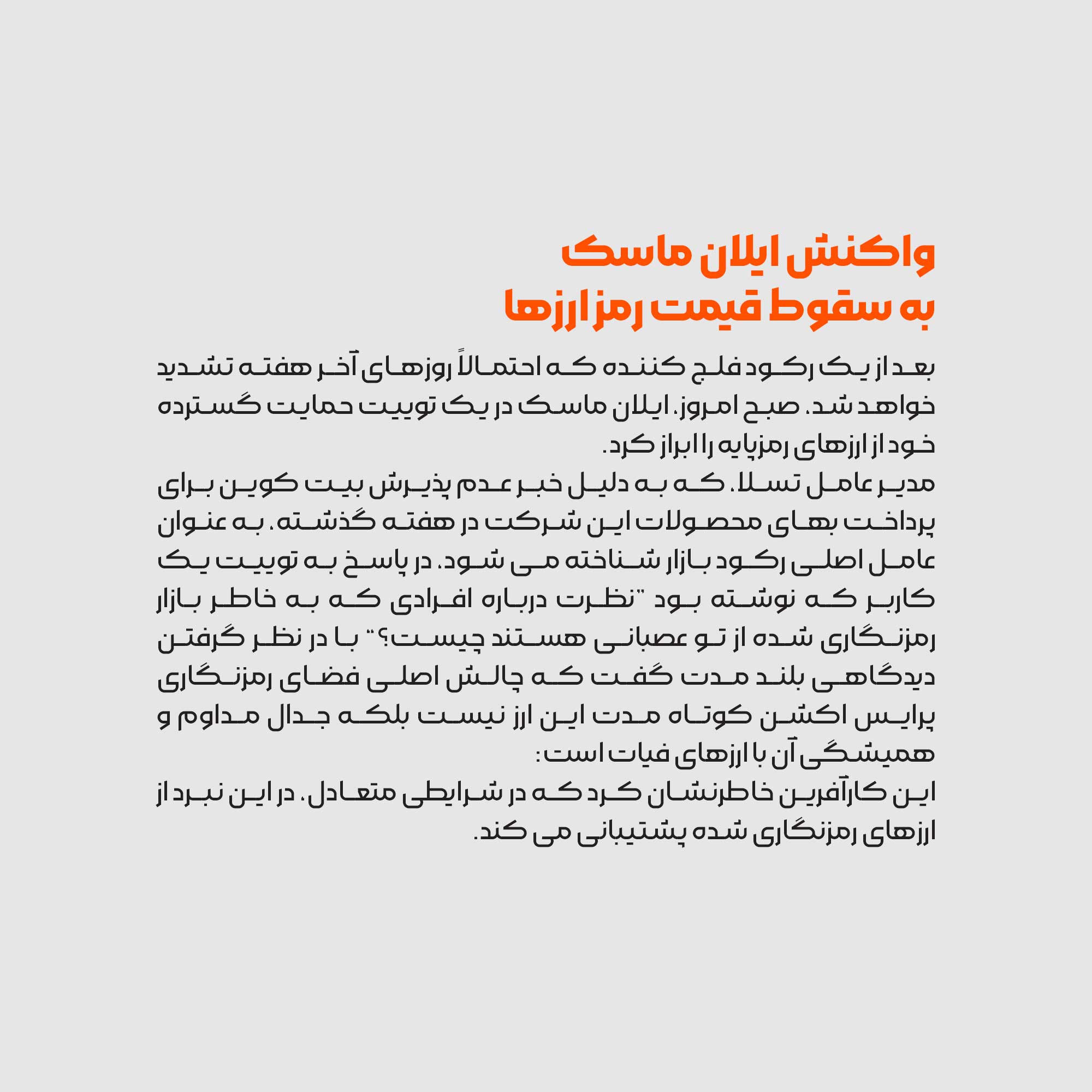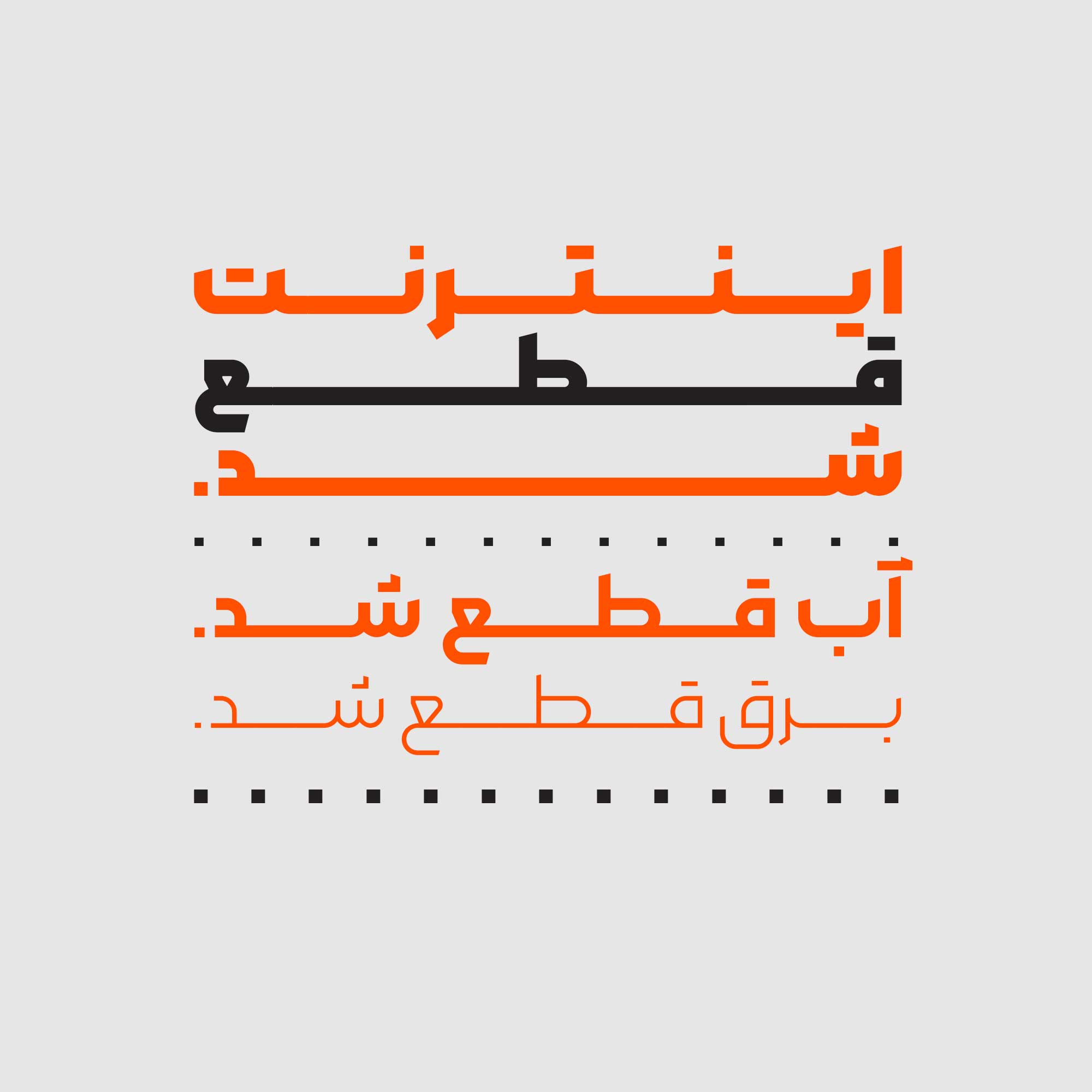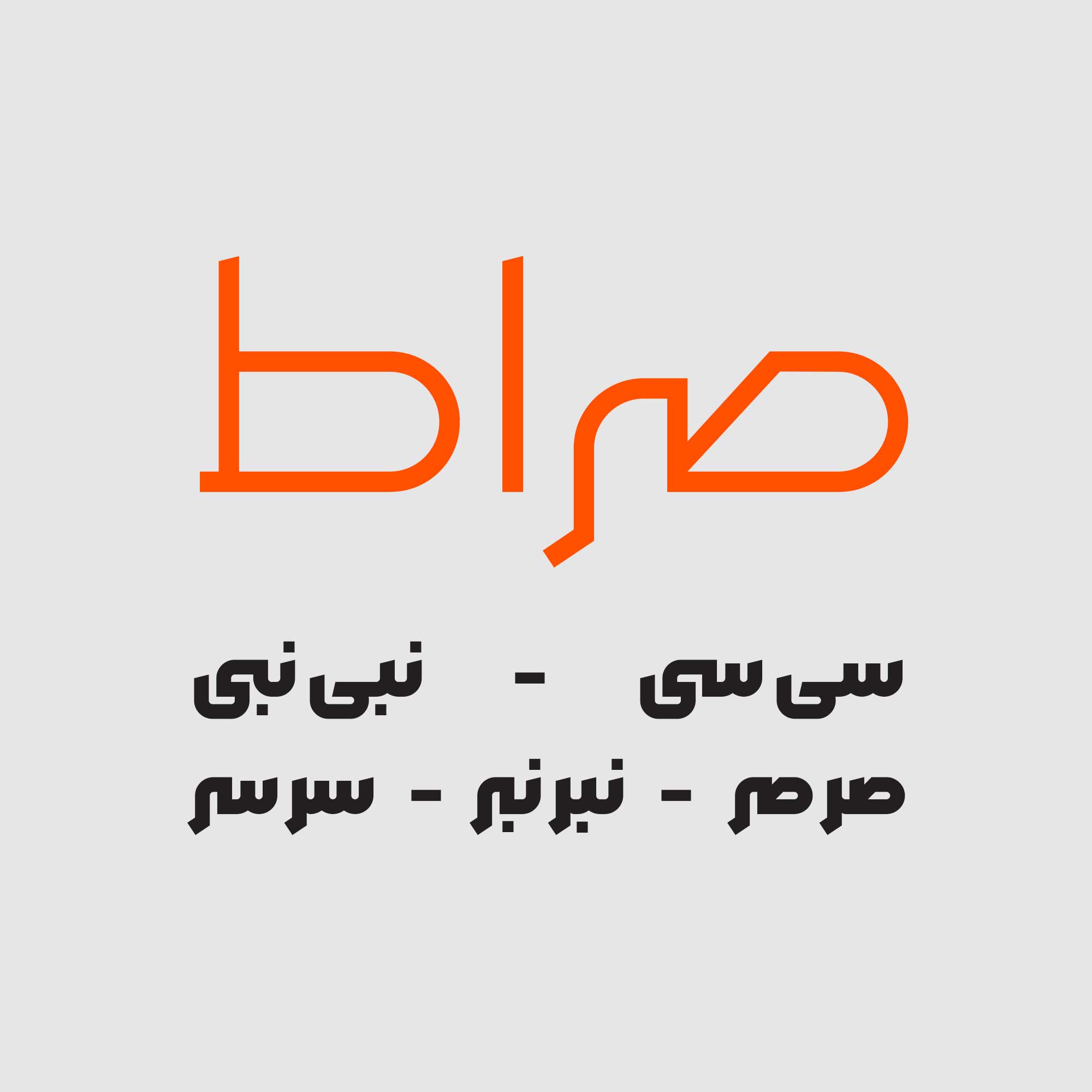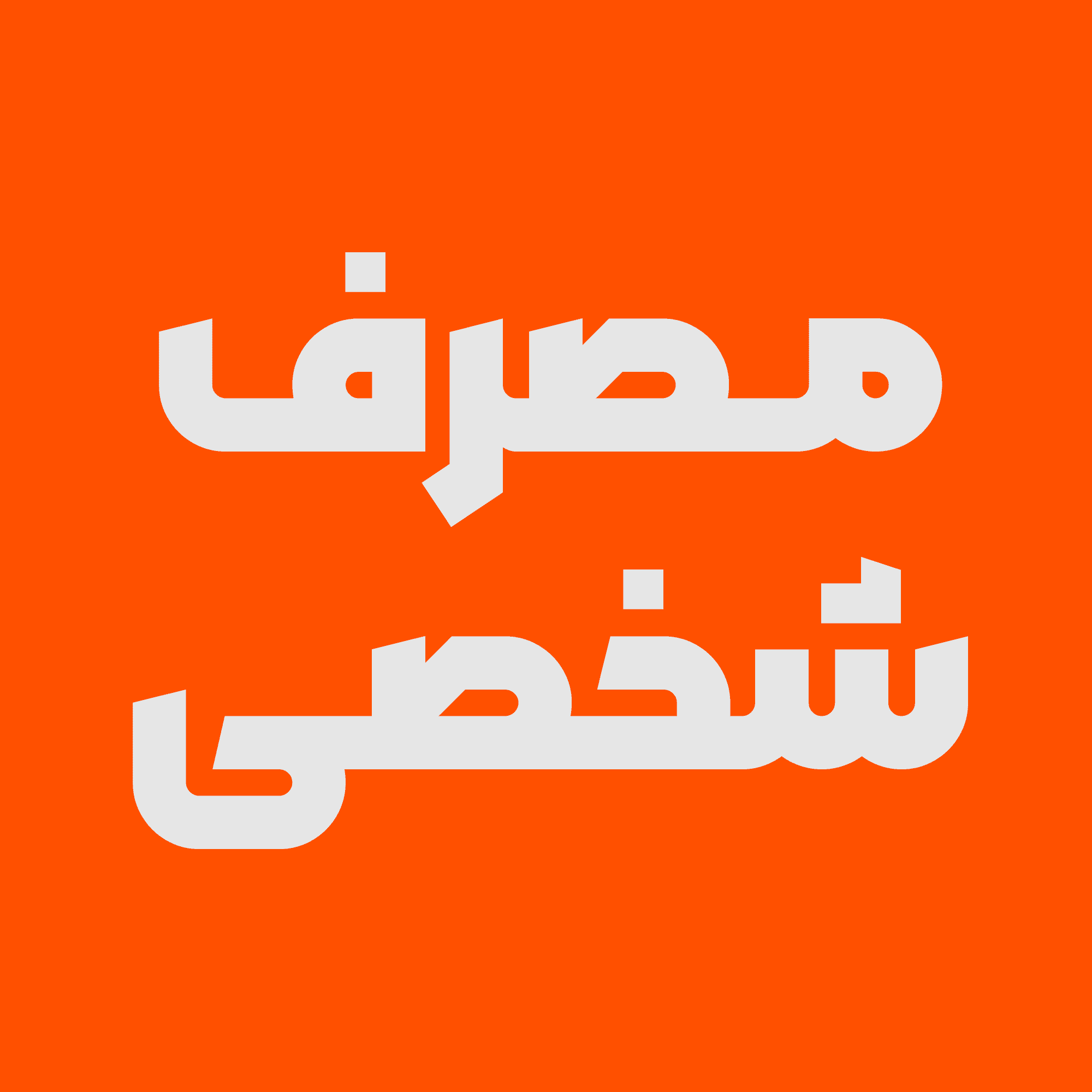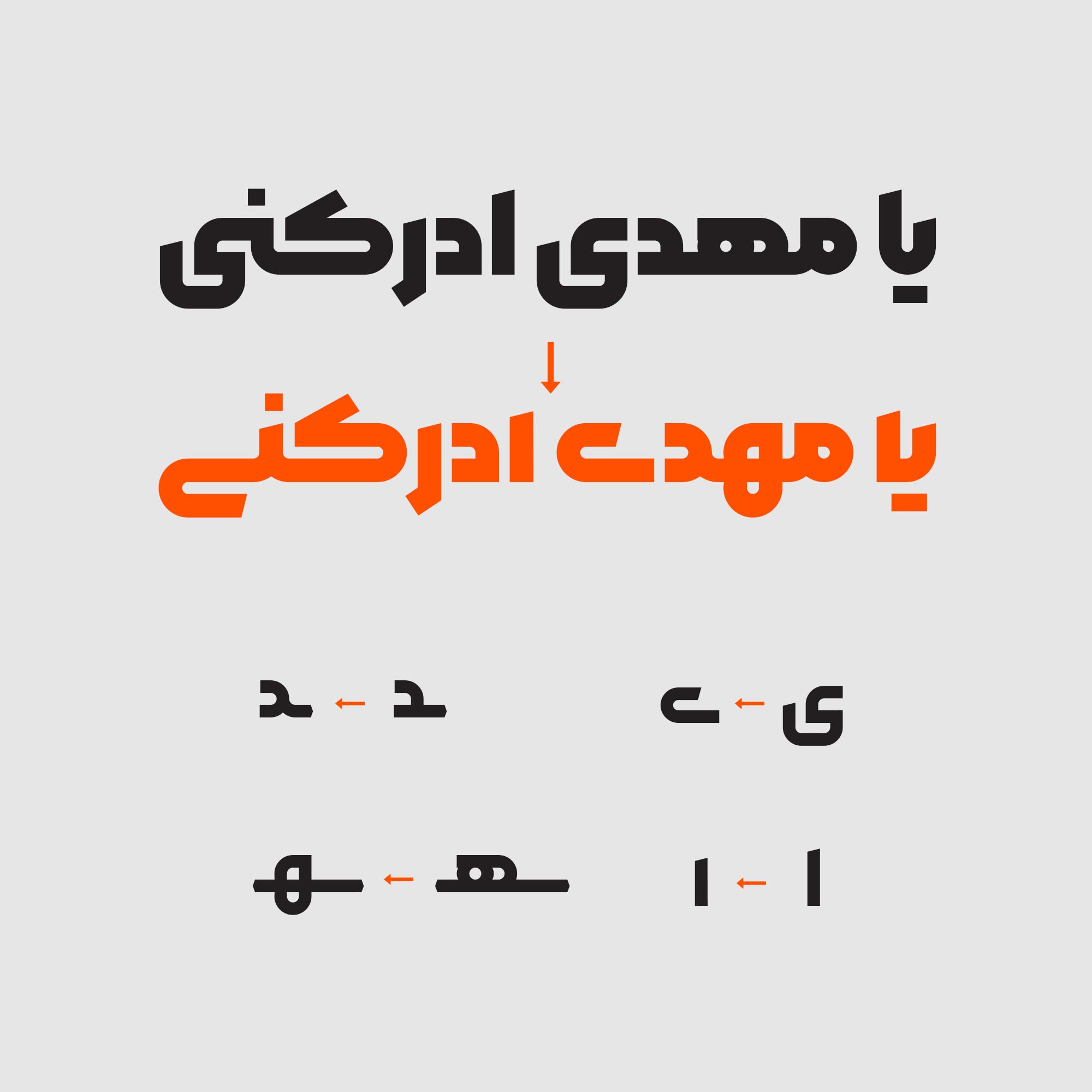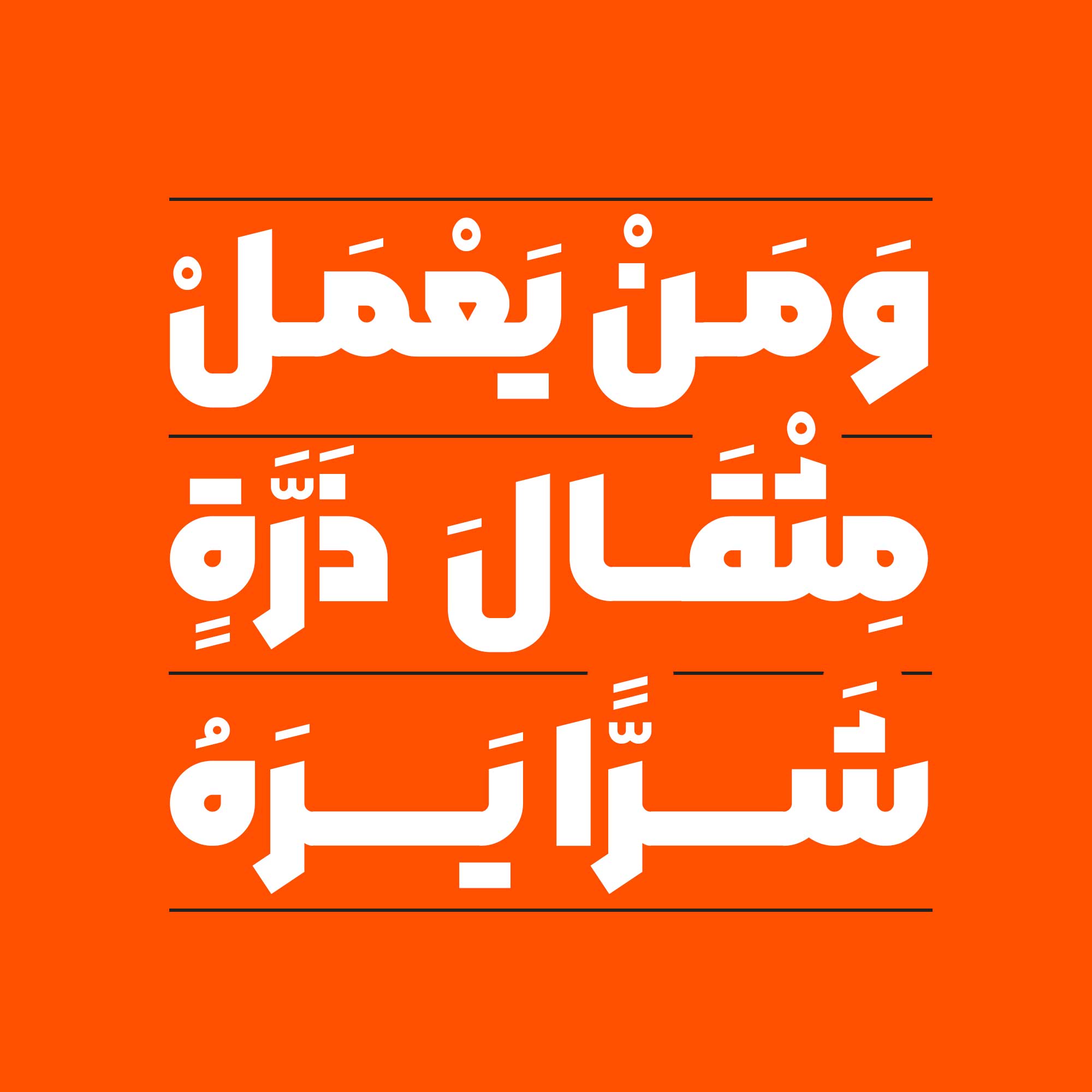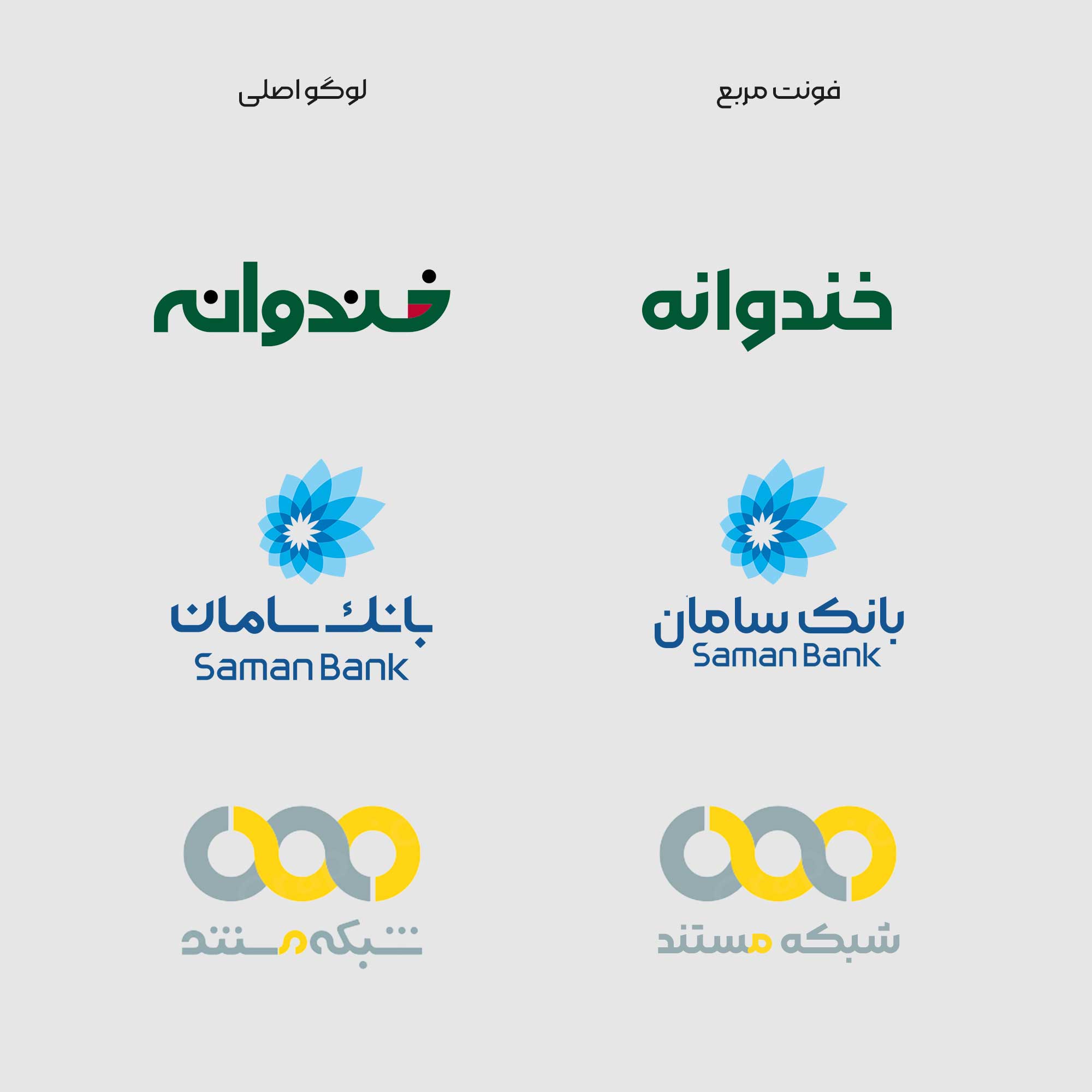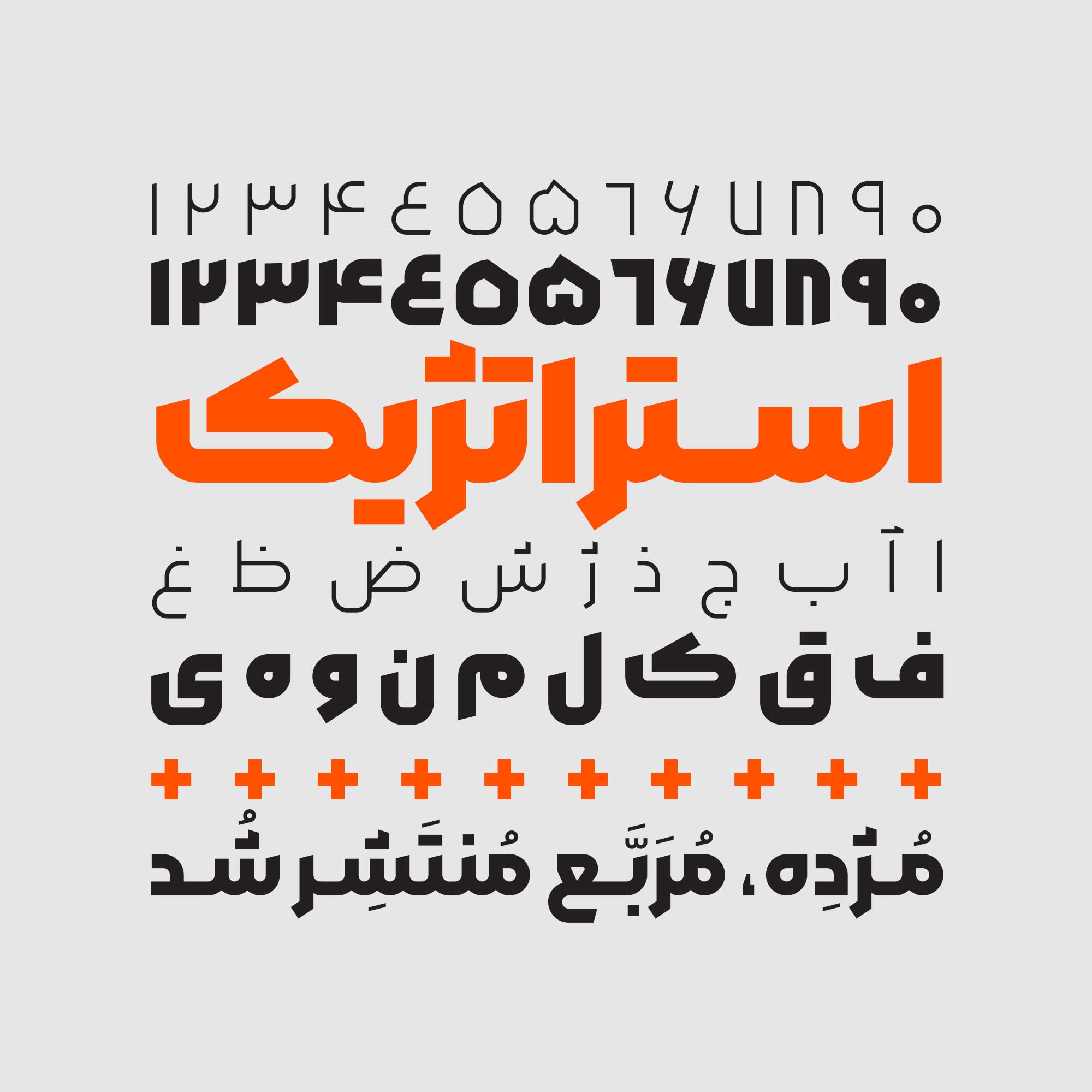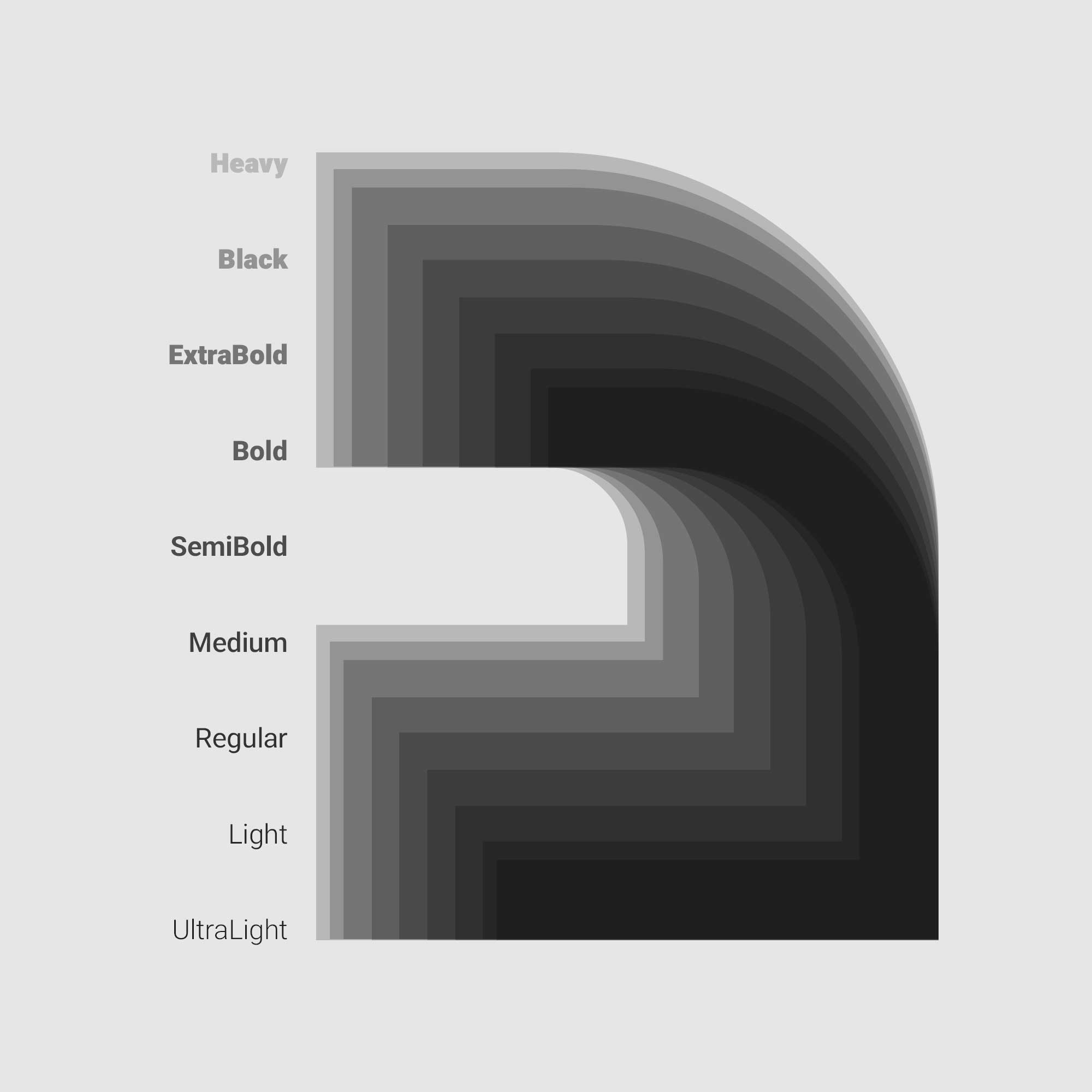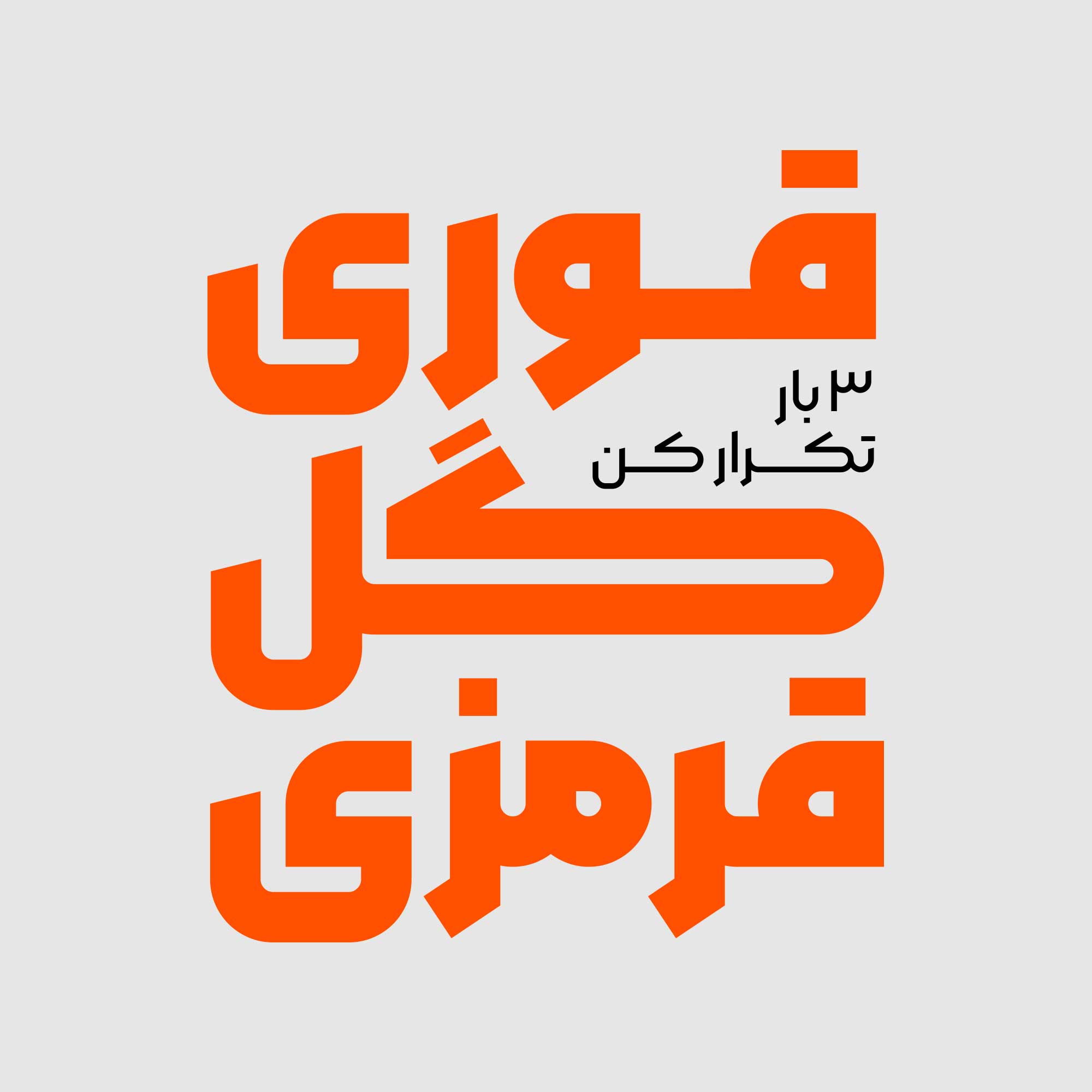
فونت مربع در سه زبان فارسی، عربی و انگلیسی قابل استفاده است. فونت Roboto به دلیل شباهت فرمی مکمل مربع شده است.
فونت مربع با دقت و سختگیری زیادی بر اساس شبکهای از شکلهای مربع و دایره طراحی شده است بنابراین شما با یک فونت هندسی تمام عیار مواجه هستید.
خانواده فونت مربع
خانواده فونت مربع شامل ۹ وزن است از خیلی نازک UltraLight تا سنگین Heavy.
دقت زیادی شده است تا روند تغییر وزن حروف فارسی با انگلیسی مطابق باشد.
این تنوع وزن امکانات زیادی برای ایجاد سلسله مراتب (هایرآرکی) در متن به شما میدهد.
هایرآکی مهمترین فاکتور برای ایجاد یک تایپوگرافی جذاب در طراحی پوسترها و کاورهاست.
فونت متغییر
فونت متغییر تکنولوژی جدیدی در ساخت فونت است که به شما این امکان را میدهد که همهی وزنها و استایلها را در قالب یک فونت در اختیار داشته باشید.
Weight : این متغیر ضخامت نوشته را تعیین میکند که حداقل آن 250 و حداکثر آن 900 است.
kashida : این متغیر در حروف اول و میانی کشیدگی ایجاد میکند.
با این متغییر میتوانید کل کلمات یک سطر را به یک نسبت عریض کنید.
به کمک متغییر کشیده خیلی راحت و سریع میتوانید سطرها را همتراز کنید.
ترکیبات اختیاری
حروف جایگزین
اعداد فارسی/انگلیسی
جابجایی نقطهها
در فونت مربع نقطههای حروف به نسبت حرف قبل و بعد خود بهترین جایگیری را خواهند داشت.
کاربرد فونت مربع در گرافیک تجاری
فونت مربع برای طراحی پوسترهای تجاری، طراحی کاورها و اسلایدهای اینستاگرام و کلا هر موضوعی که معاصر و امروزی باشد مناسب است.
کاربرد فونت مربع در طراحی ورد مارک Wordmark
بسیاری از کسب و کارهای کوچک توانایی پرداخت هزینه یک لوگوتایپ اختصاصی را ندارند.
در این مواقع استفاده از یک فونت هندسی مانند مربع به عنوان ورد مارک، انتخاب هوشمندانه و به صرفهتری است.